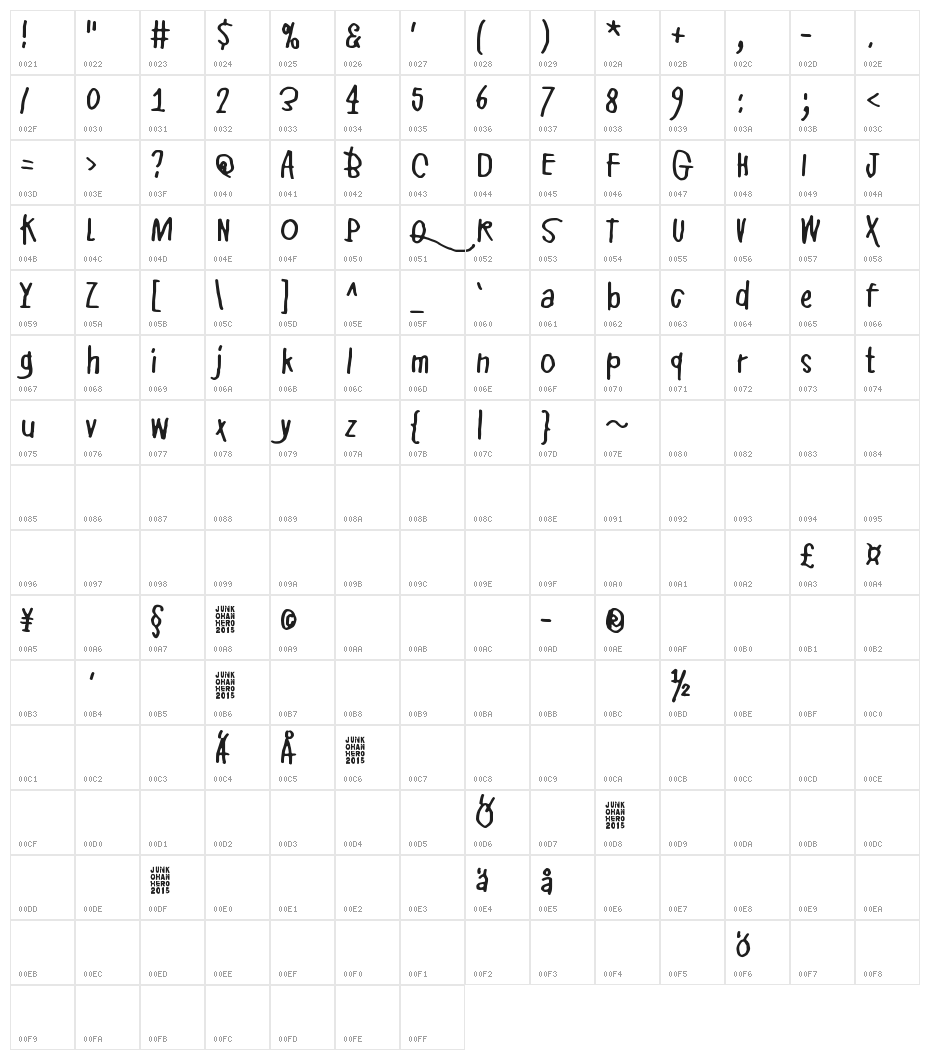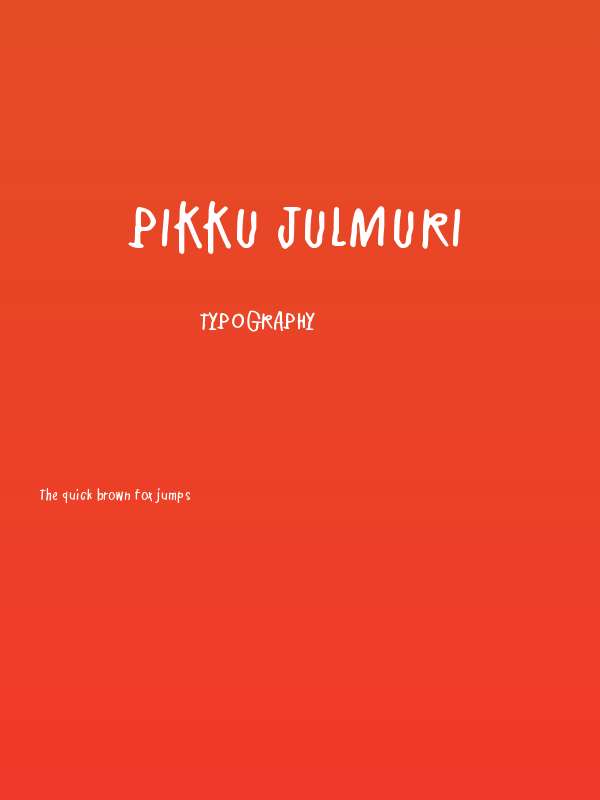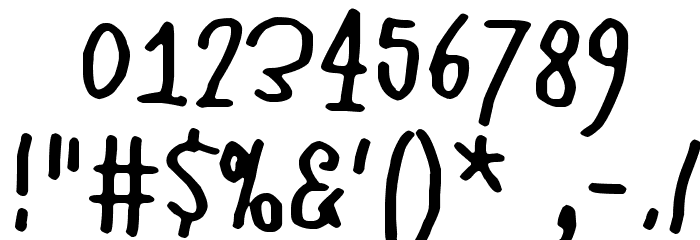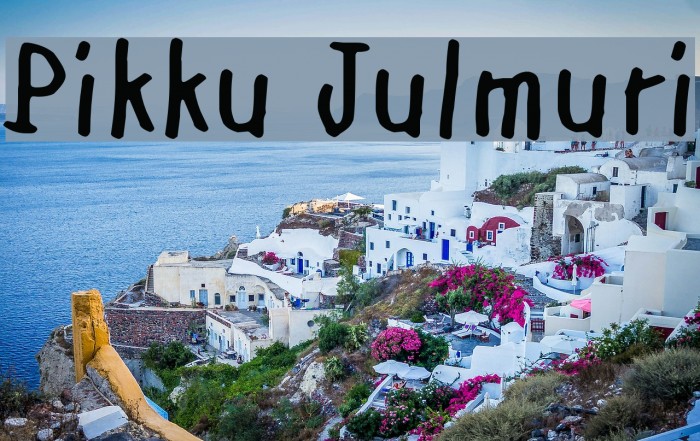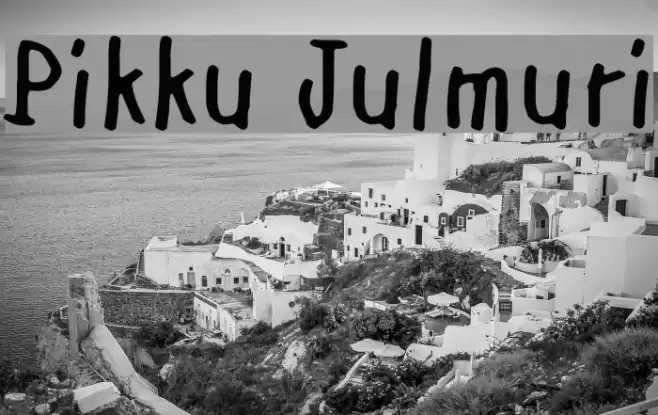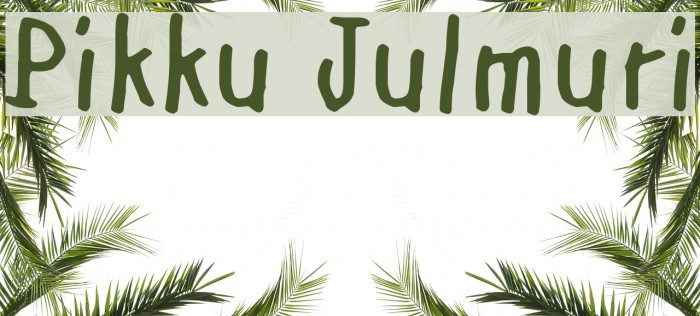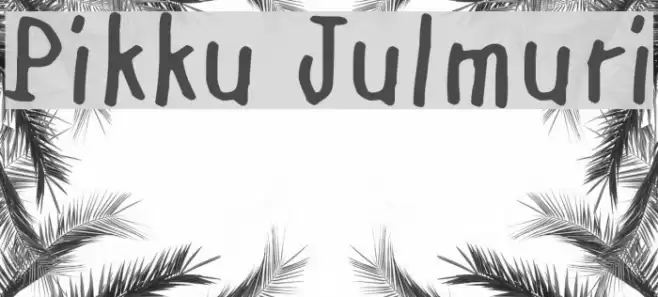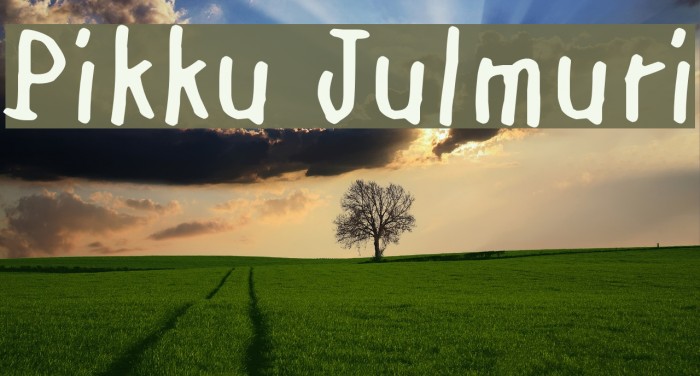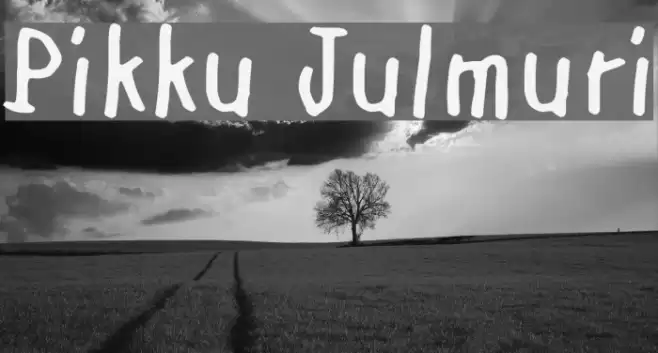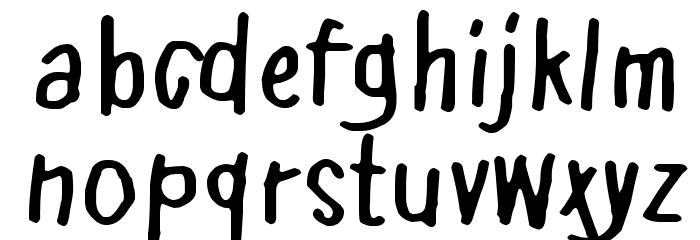
Pikku Julmuri Font
| Style général | Casual |
| Cas d'utilisation | Headlines, Informal text, Creative projects |
| Projets proposés | Ideal for greeting cards, children's books, playful branding, and creative posters. |